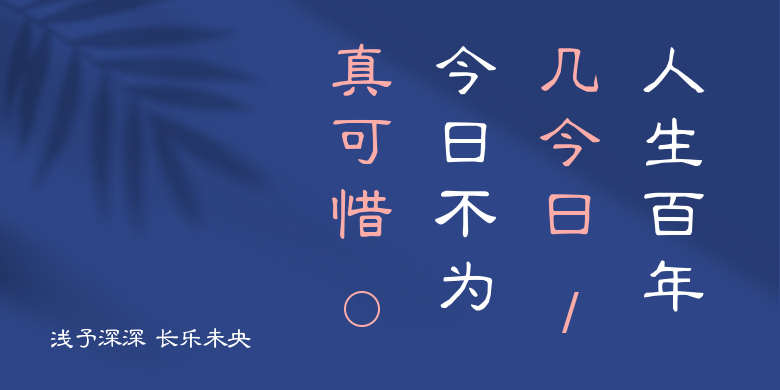
浅予深深 长乐未央
浅予深深 长乐未央,这款字体结构工整、笔画清晰,兼顾美观与易读性,适用于标题、正文、海报、包装、LOGO 等多种场景。字形优雅稳定,风格百搭耐看,适配日常排版与创意设计,让文字呈现更舒适、更具质感。浅予深深 长乐未央一笔一画,皆是细节,以均衡的比例、流畅的线条打造舒适视觉体验,字形端正大气,风格简约现代。无论是商业设计、品牌宣传还是日常排版,都能轻松驾驭,让文字更有格调与力量。浅予深深 长乐未央字体下载。